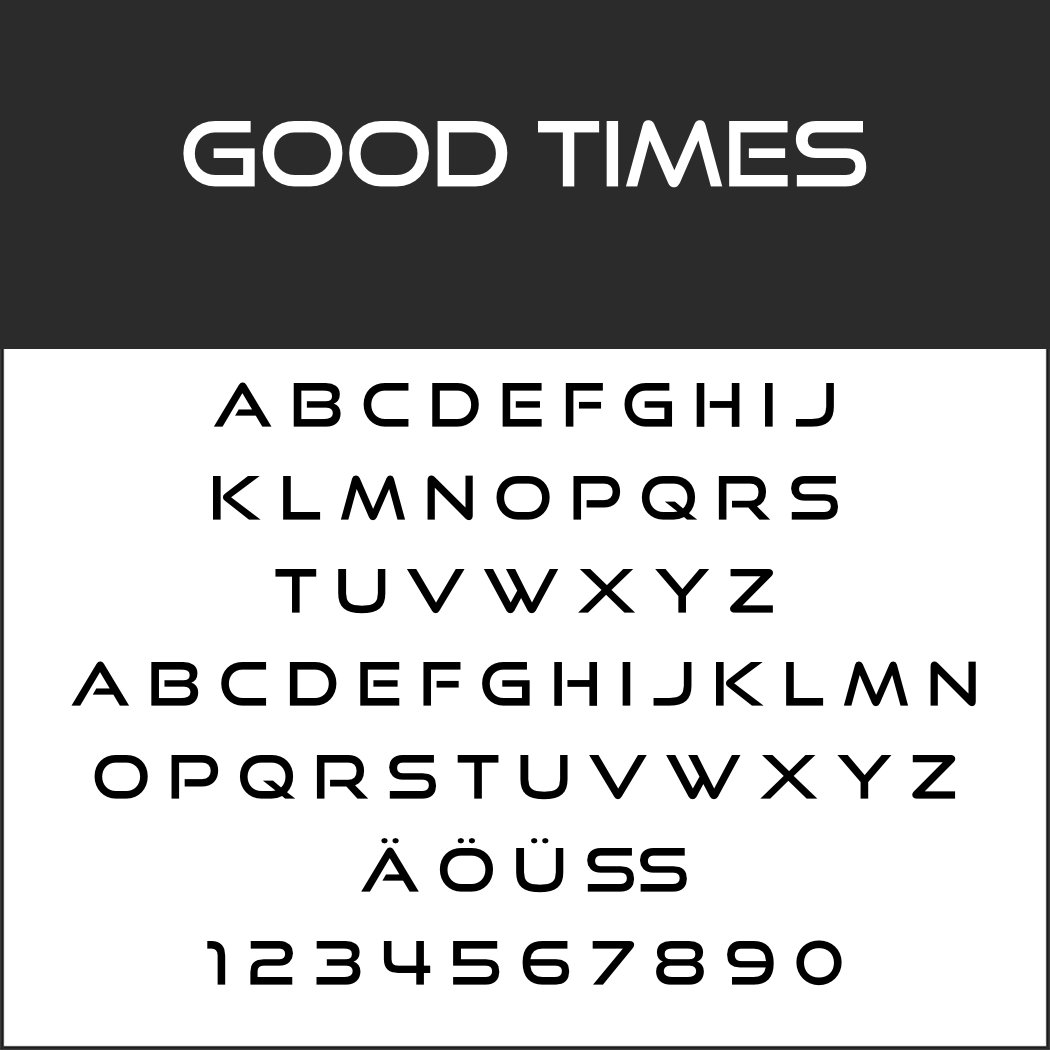
Retro-Klamotten, eine Revivalparty oder Compilations von Videospielen und Filmen: Es gibt genügend Anlässe, um eine 80er-Schriftart zu verwenden. Viele dieser Fonts wecken bei den Kunden und Nutzern sofort Assoziationen, die Sie für den Werbeeffekt nutzen können.
1980 Portable
In den 1980ern war Ska auf seinem Höhepunkt. Der Designer widmet seinen Font diesem Musikstil und lädt dazu ein, damit Poster, T-Shirts, Videos, Schilder, Logos und noch viel mehr zu erstellen.
Astron Boy
Das Videospiel Astron Belt lieferte die Vorlage für diesen Font in vier Ausführungen: Regular, mit Schatten, kursiv und mit Bewegungsstreifen.
Aurach
Inspiriert von der Sportmarke mit den Streifen entwickelte der Designer einen typischen 80er-Jahre-Font. Neben der abgebildeten Variante gibt es Aurach auch als Massiv- und Konturschrift.
Cayetano
Nicht besonders leserlich, aber eine Hommage an die Displays der Achtziger stellt diese Pixelschrift dar.
FFF Forward
Mit FFF Forward haben wir eine massive Pixelschrift, die sich vor allem auf Plakaten und Postern gut macht und sofort Erinnerungen an alte Videospiele weckt.
80er SchriftartGood Times
Die späten 1980er-Jahre und ein Hauch von Star Trek lassen grüßen: Good Times im besten Sinne.
Press Start 2P
Wer mit Arcade-Spielen von Namco groß geworden ist, bekommt bei Press Start 2P mit Sicherheit nostalgische Gefühle. Kopiert wurde die 80er-Schriftart aus Return of Ishtar.
80er SchriftartPropaniac
Inspiriert von einem Plattencover der Pointer Sisters vereint die 80er-Schriftart Propaniac in sich Postmoderne und 1980er.
Still Time
Ein bisschen Horror, ein bisschen Rock ’n‘ Roll – der Retro-Font Still Time ist vielseitig einsetzbar.
80er SchriftartVenus Rising
Nahezu quadratisch präsentiert sich die 80er-Schrift Venus Rising, das an die frühen 1980er und ausgehenden 1970er erinnert.
Zorque
Auch mit Zorque lebt der Stil der Videospiele aus den 1980ern wieder auf. Dieser Font ist vor allem für kurze Schlagwörter geeignet.